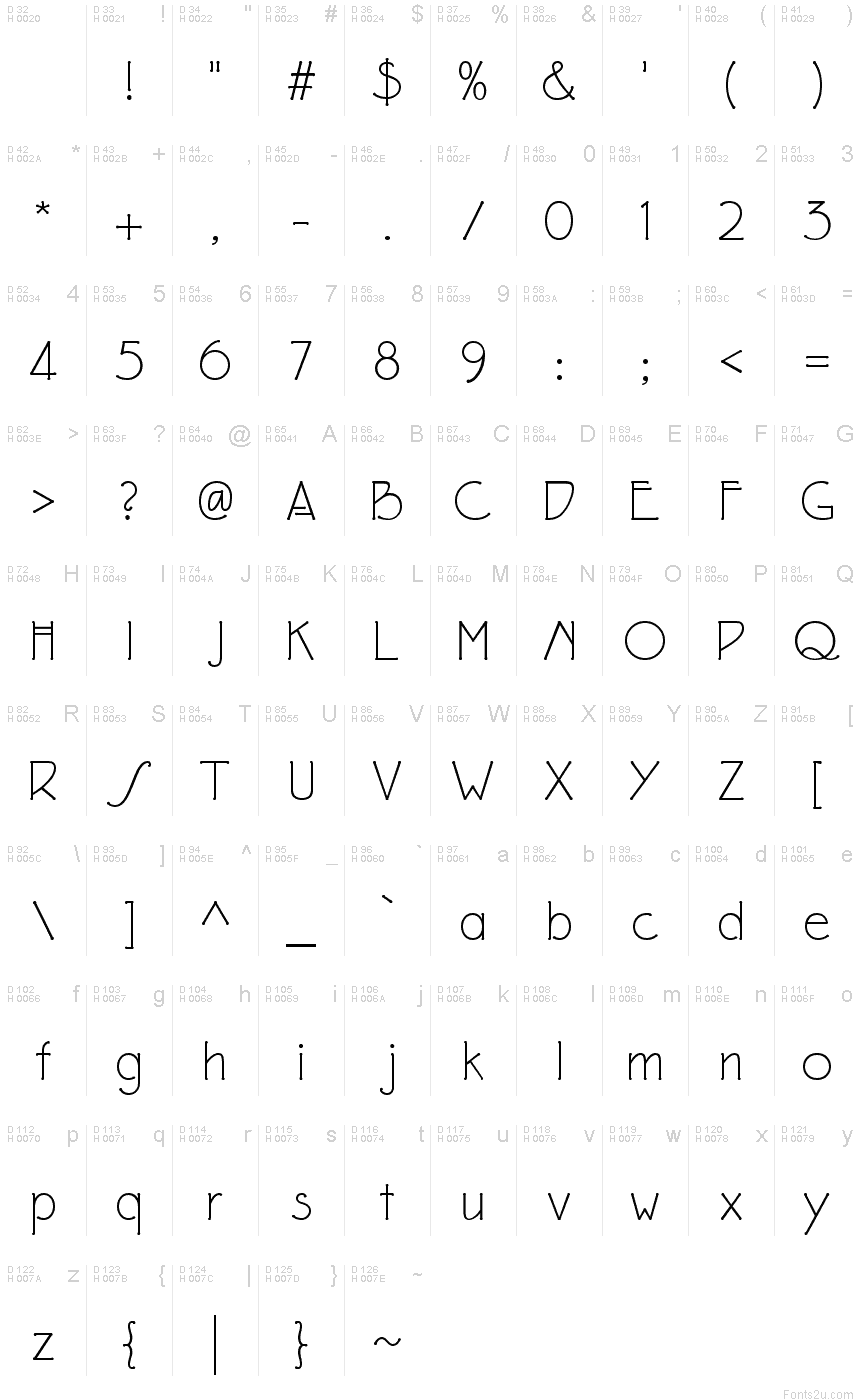
EaglefeatherFormalLight
Eaglefeather Formal Light to darmowy, bezszeryfowy krój pisma w stylu retro, który sprawia wrażenie delikatnego tuszu naniesionego pewną ręką. Jego linie są smukłe i równe, a miękkie, płynne krzywizny nadają każdemu słowu cichą, elegancką lekkość. Ten lekki wariant, wywodzący się z rodziny Eaglefeather Formal, wnosi powiew świeżości i wyrafinowania, zachowując jednocześnie nowoczesny i przystępny charakter.
Stosując Eaglefeather Formal Light, uzyskasz pełen wdzięku rytm, który doskonale sprawdzi się w papeterii ślubnej, logotypach butików, plakatach okolicznościowych, projektach opakowań, tytułach redakcyjnych oraz minimalistycznych grafikach do mediów społecznościowych. Dzięki dużym odstępom pismo pozostaje przejrzyste i czytelne, nawet w większych rozmiarach, gdzie w pełni ujawniają się jego subtelne detale. Aby uzyskać profesjonalny efekt, połącz ten darmowy font z prostym, geometrycznym krojem bezszeryfowym w tekście głównym, a Eaglefeather Formal Light wykorzystaj do nazw, nagłówków i kluczowych haseł.